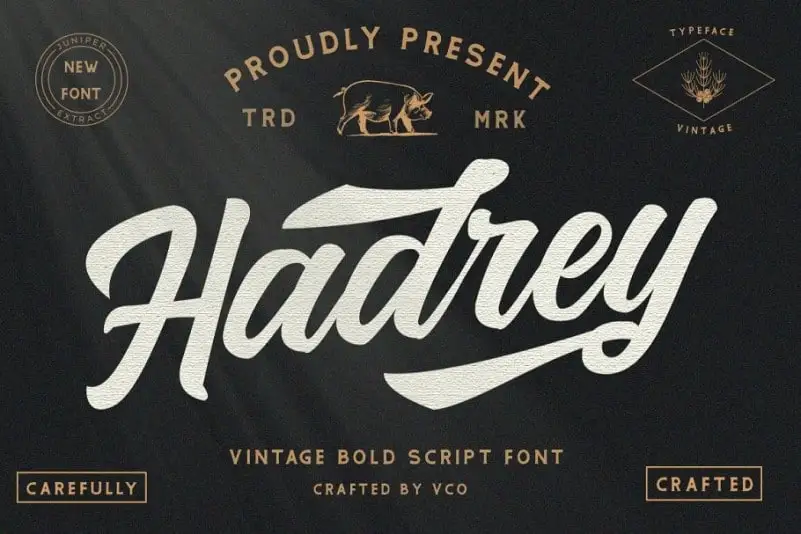
Hadrey – Vintage Script Font – Fonte Grátis
Hadrey - Vintage Script Font
Hadrey é uma fonte script vintage que se destaca por sua elegância arcaica e seus detalhes rúnicos. Inspirada nos estilos tipográficos retro dos anos 70 e 80, ela oferece tanto versões limpas quanto rough, proporcionando um tom de nostalgia perfeita para criações de design modernas. Convidativa a quem busca um estilo vintage sem perder a força da boldness que o moderno requere, Hadrey traz uma combinação única de estilos arcaicos e retro em cada caracter. Suas formas não-perfeitas dão vida à sua essência natural, tornando-a perfeitamente adaptável para criações como logotipos tradicionais, rótulos, embalagens, desenhos para camisetas e muito mais. Ideal tanto para iniciantes quanto para profissionais, Hadrey é uma fonte script vintage que traz um toque de nostalgia ao seu design gráfico.